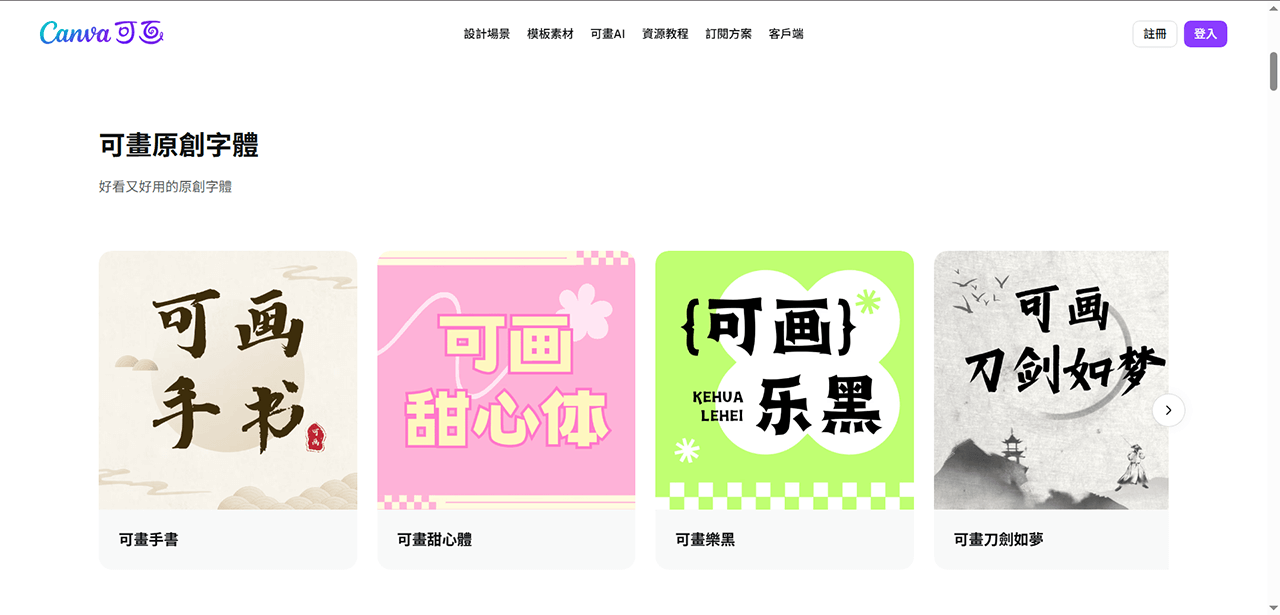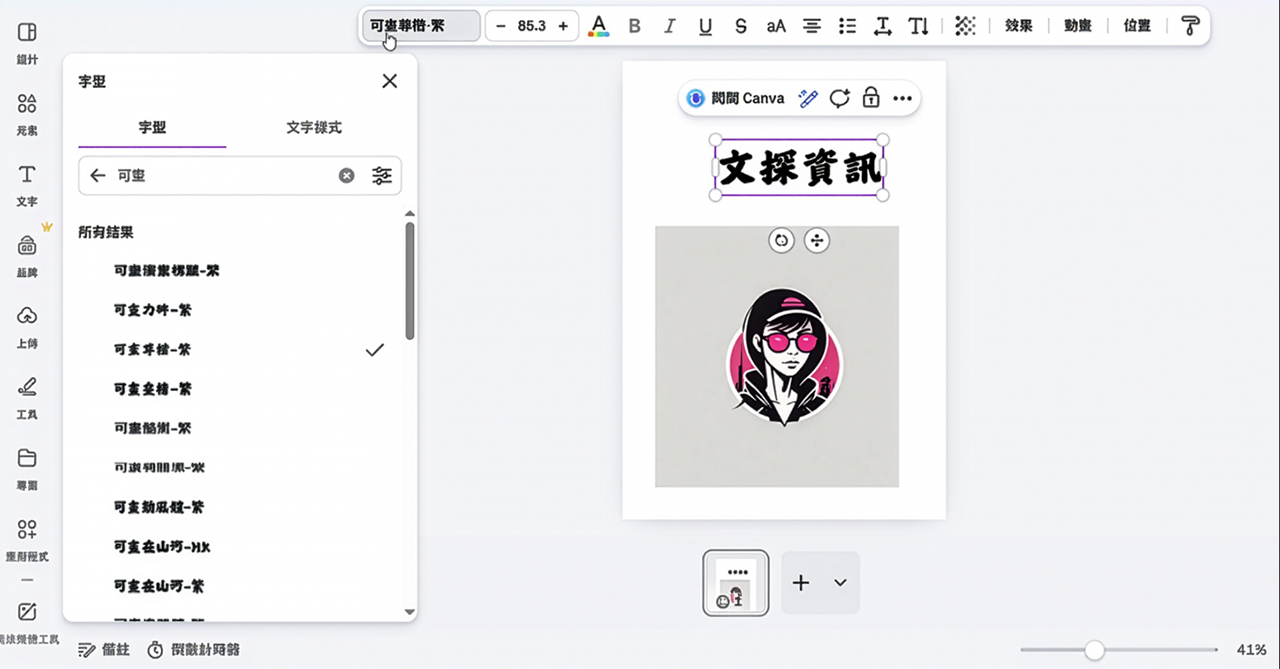
Canva「可畫」線上設計平台上提供的中英文字體庫(Fonts)
全球廣泛使用的線上設計平台 Canva,它提供的字體庫裡面,除了來自開源字型如思源字體 (Noto)、芫荽字體等之外,也委託專業的字體公司量身打造 Canva 自家品牌的字體庫。在英文字型方面是由知名設計公司 Colophon Foundry 打造的,而中文字型部分則與中國知名的字體設計公司 「漢儀字庫」(Hanyi Fonts)深度合作開發。
Canva 與 Colophon 於 2021 年合作開發了名為 Canva Sans 的無襯線字體家族,涵蓋9 款樣式,包含不同的字體,也區分了Text 和Display 兩種視覺字號。Colophon Foundry 現已被知名的蒙纳家族/Monotype 收購。
Canva 於 2018 年正式進入中國市場(Canva.cn),並開始與當地的字體廠商「漢儀字庫」合作,大約是在 2020 年至 2021 年間推出簡體中文字型的「Canva 可畫字體庫」系列(如「Canva 可畫黑體」)。這個中國特有版本的 Canva 叫做「可畫」,它有別於 Canva.com 的全球版,而台灣和港澳地區都屬於全球版。
「可畫字體庫」(如 Canva 可畫黑體、Canva 可畫細黑),其實是 Canva 與漢儀字庫深度客製的版本。如果您在漢儀官網尋找,應該是找不到完全同名的字體。
這幾年來,隨著 Canva 全球化進程,這些針對簡體中文市場開發的字體,也逐步在全球版 Canva.com 網站上線,並標註「繁體」以方便港澳台灣用戶使用。而且中文的字體庫從初期的十餘套簡體中文字體,已擴充至數十套簡繁體的中文字體,而且持續開發中。